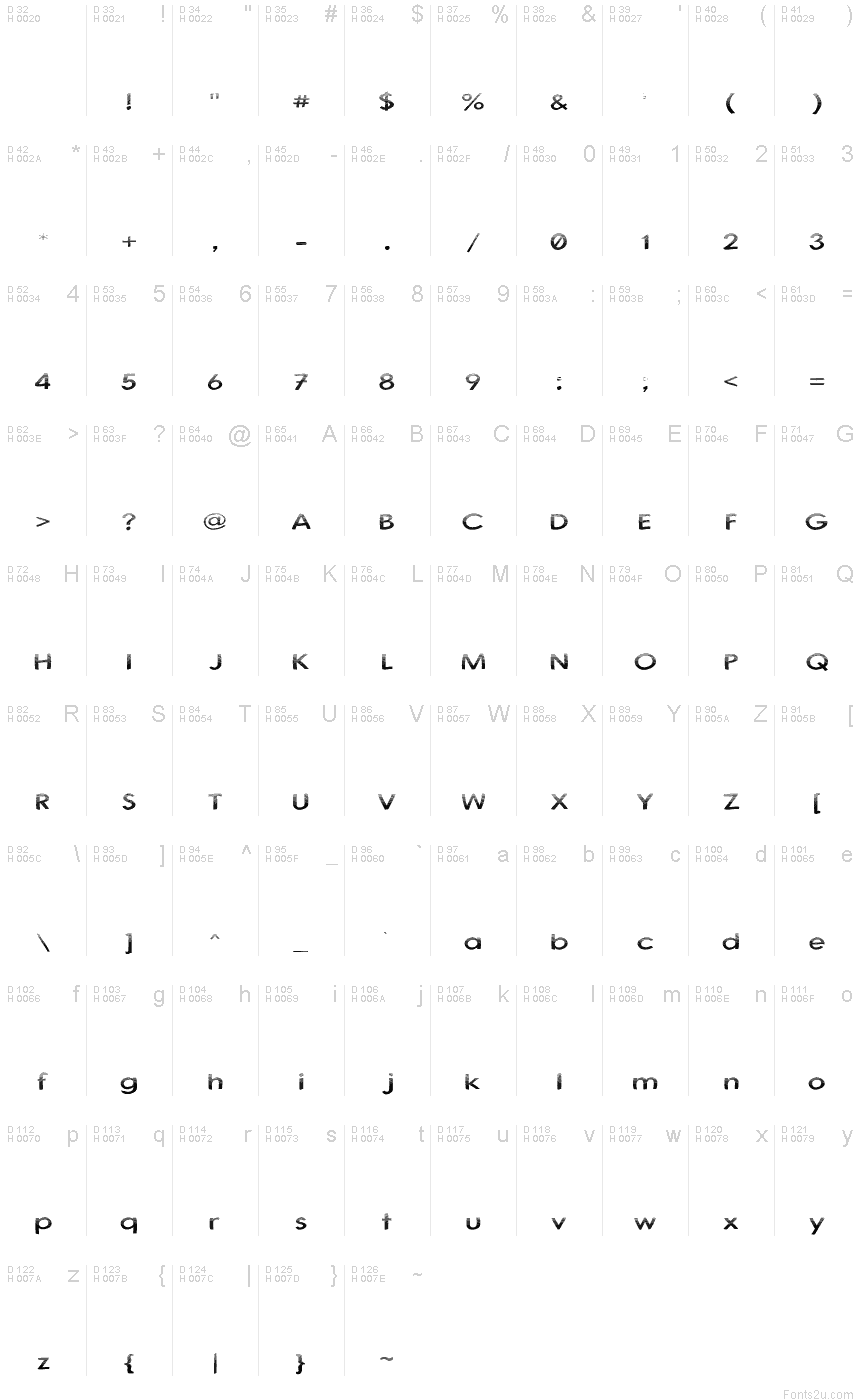
Australian Sunrise par Gemfonts98 est une police d'affichage gratuite et distordue, empreinte d'une ondulation brûlée par le soleil qui donne à vos mots un aspect à la fois artisanal et flou, comme sous l'effet de la chaleur. Les formes épaisses s'inclinent et s'étirent là où on ne les attend pas, évoquant une enseigne vue à travers un air tremblant. Cela confère aux titres une allure ludique et légèrement indisciplinée, sans jamais basculer dans le chaos illisible.
Utilisez Australian Sunrise pour vos titres d'affiches, pochettes d'albums, branding surf ou skate, flyers de festivals, impressions sur t-shirts, stickers ou miniatures YouTube percutantes. Elle excelle sur les phrases courtes où son rythme déformé peut s'exprimer pleinement : affichez-la en grand et laissez-la respirer. Associez cette police gratuite à une police sans empattement néo-grotesque épurée pour le corps de texte afin de garder un ensemble net.